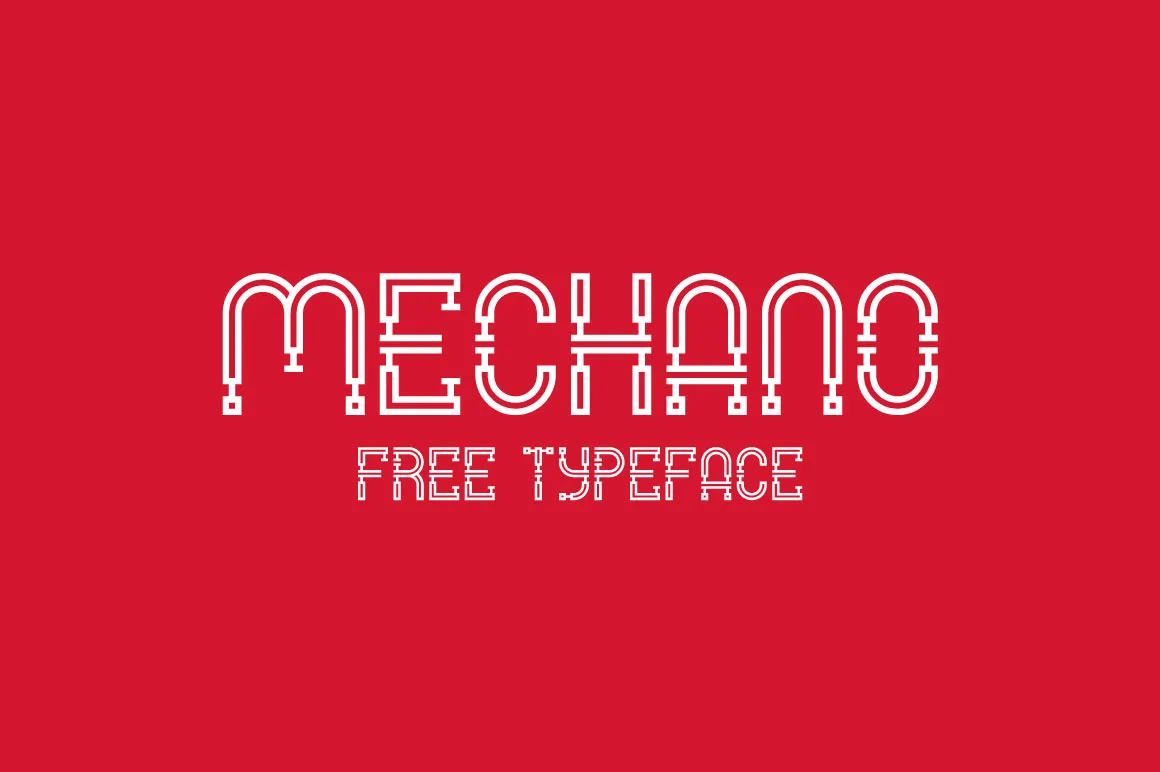
A fonte ‘Mechano Font’ é uma criação do designer Hamilton, apresentada aqui na categoria de Fonts Decorativas. Este custom font oferece um estilo único, combinando elementos industriais ou geométricos de forma atraente e versátil. Ideal para projetos criativos em desenvolvimento, esta font não só adiciona diversão à sua identidade visual, mas também eleva seu trabalho ao próximo nível. Descarregue agora ‘Mechano Font’ e descubra o que essa customização pode fazer para tornar seus projetos ainda mais memoráveis e atraentes. Enjoy 😉